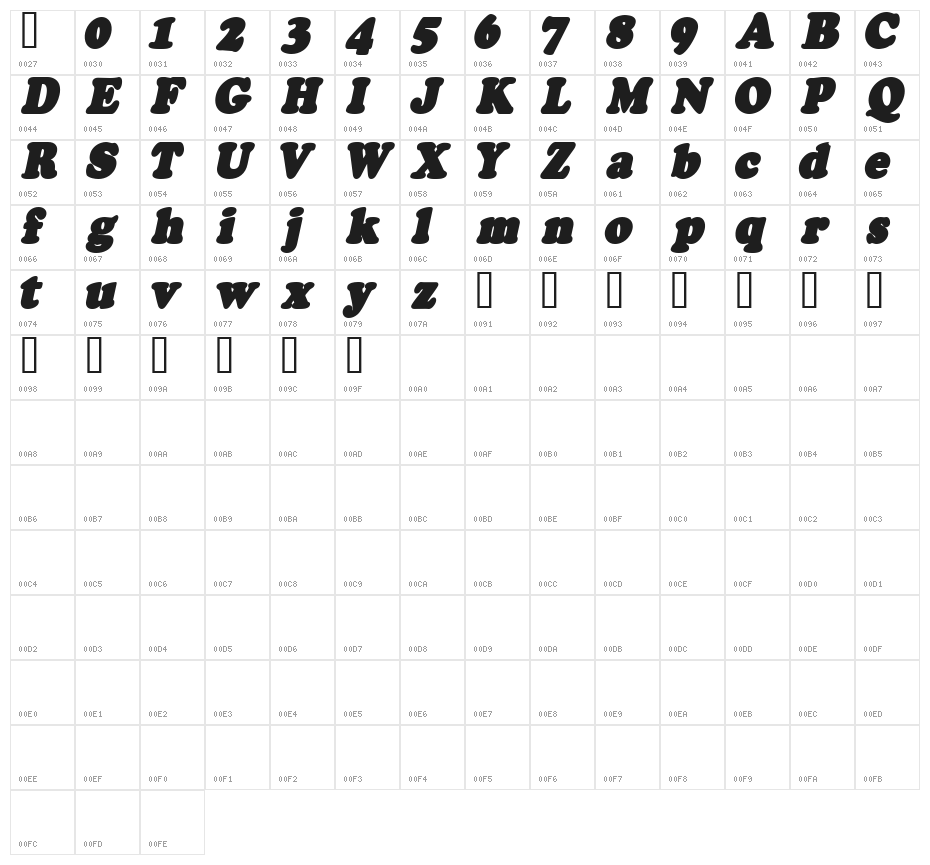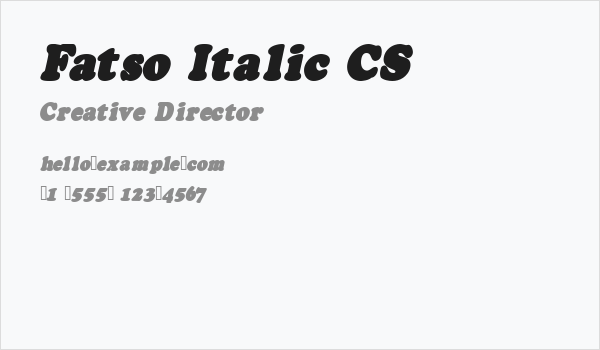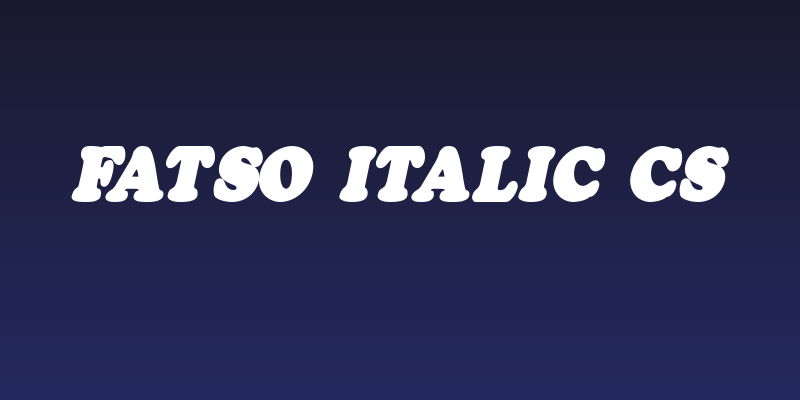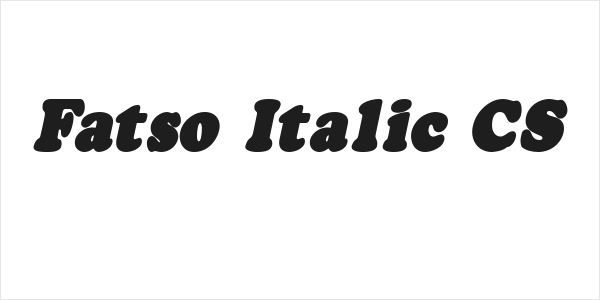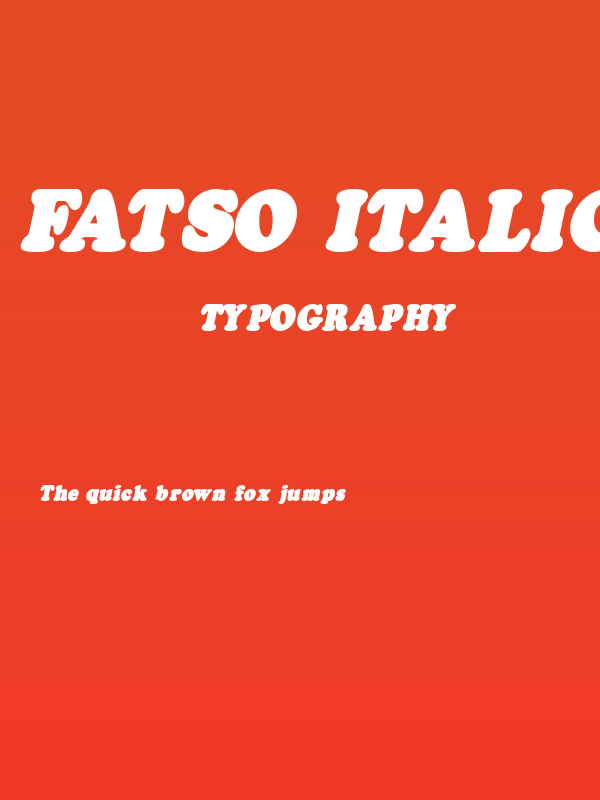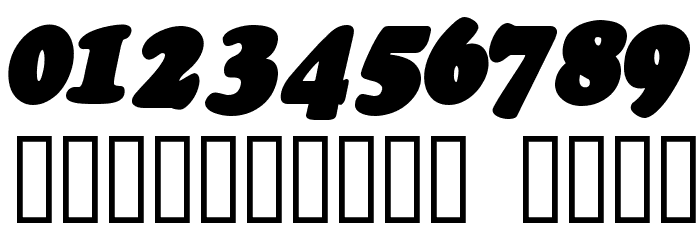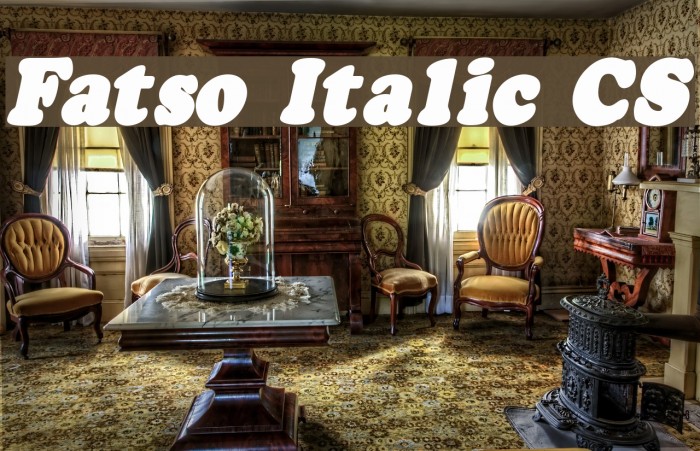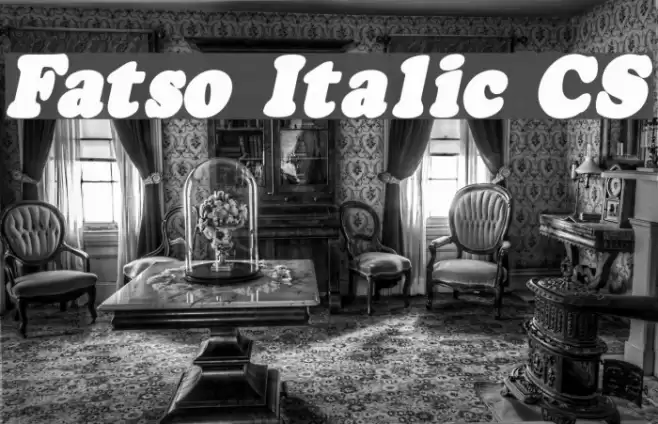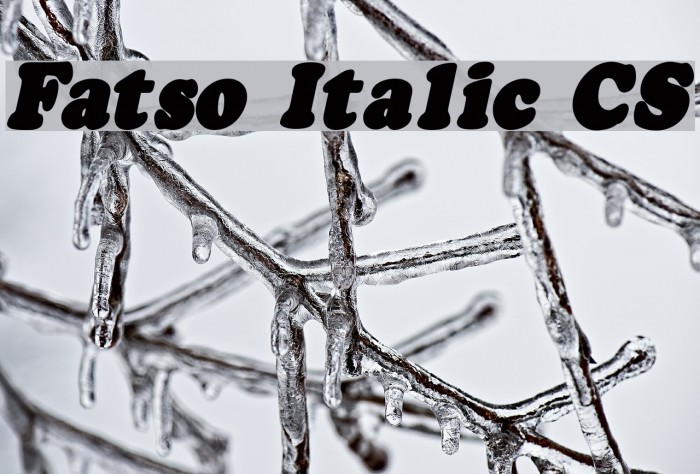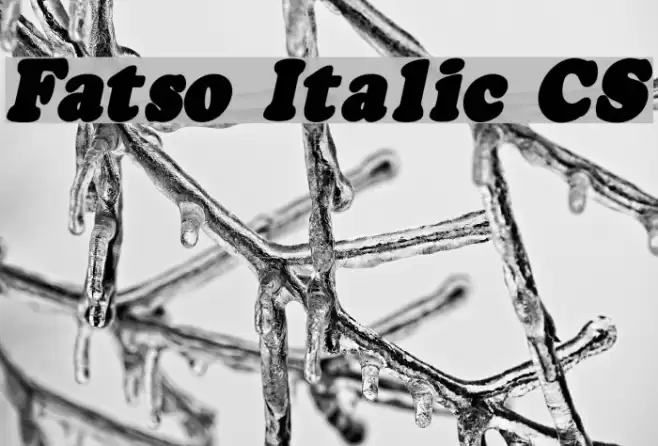
Fatso Italic CS Font
| النمط العام | Playful, Energetic |
| مشاريع مقترحة | Ideal for children's books, playful branding, event posters, and creative advertising. |